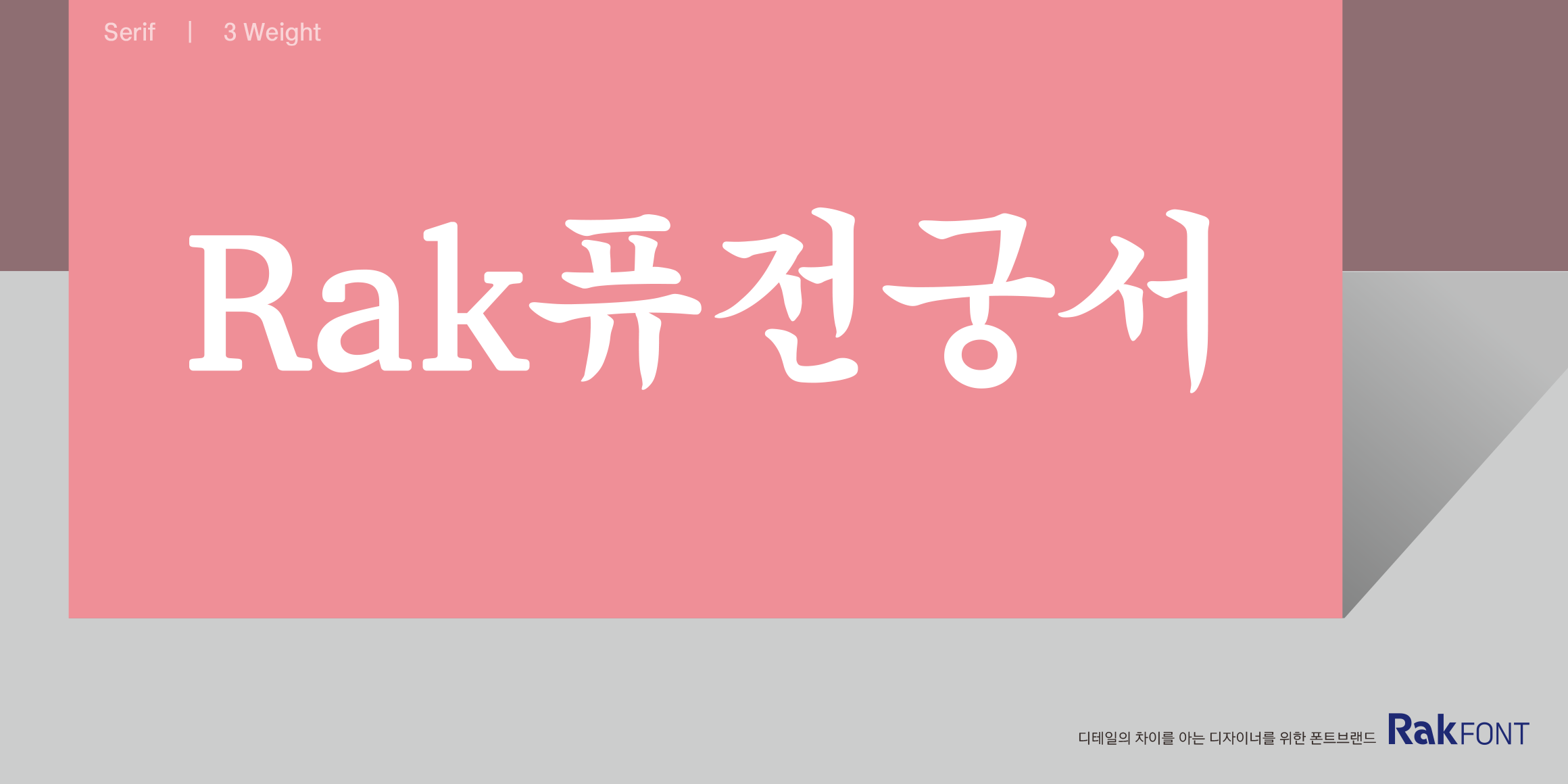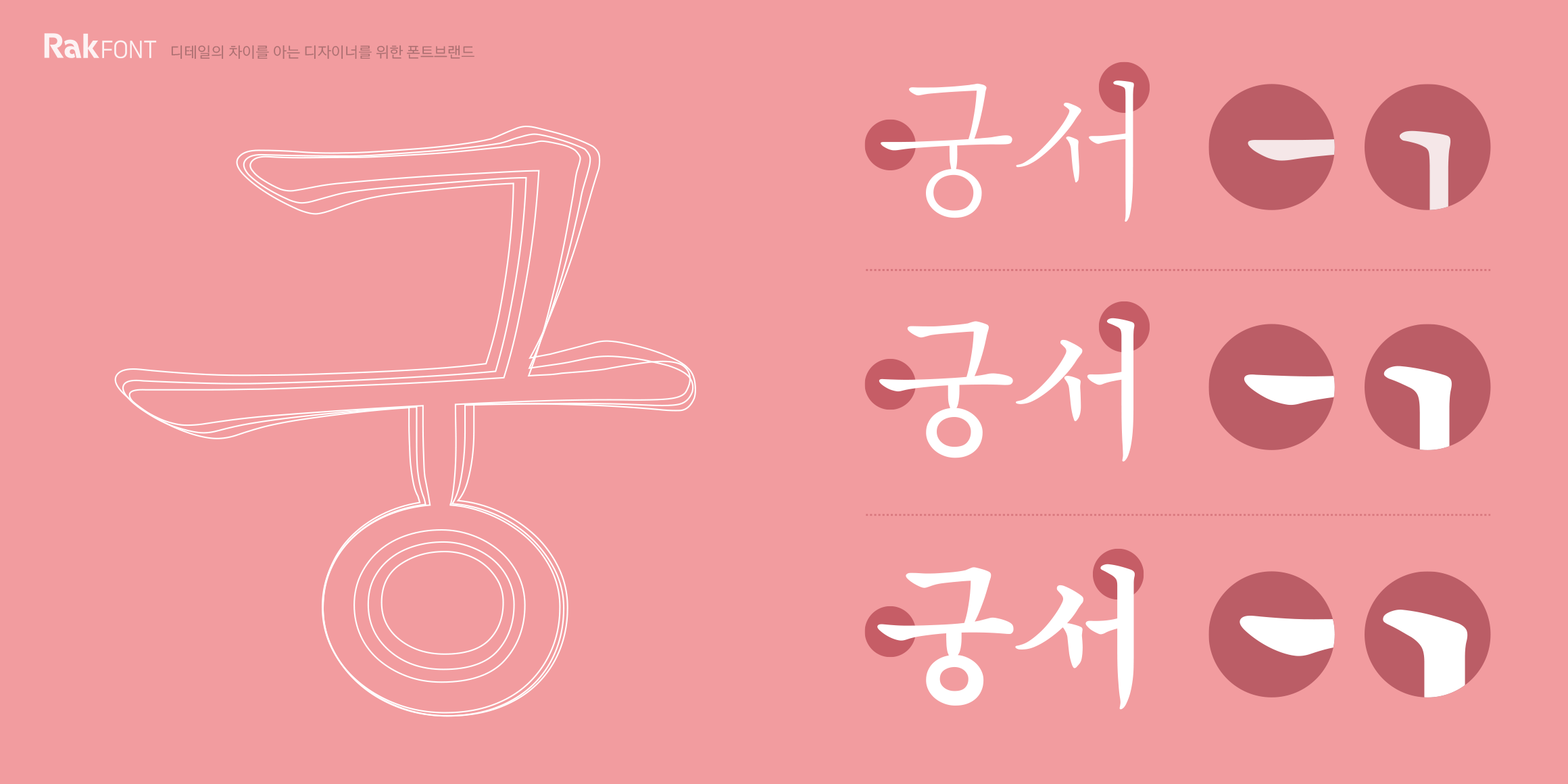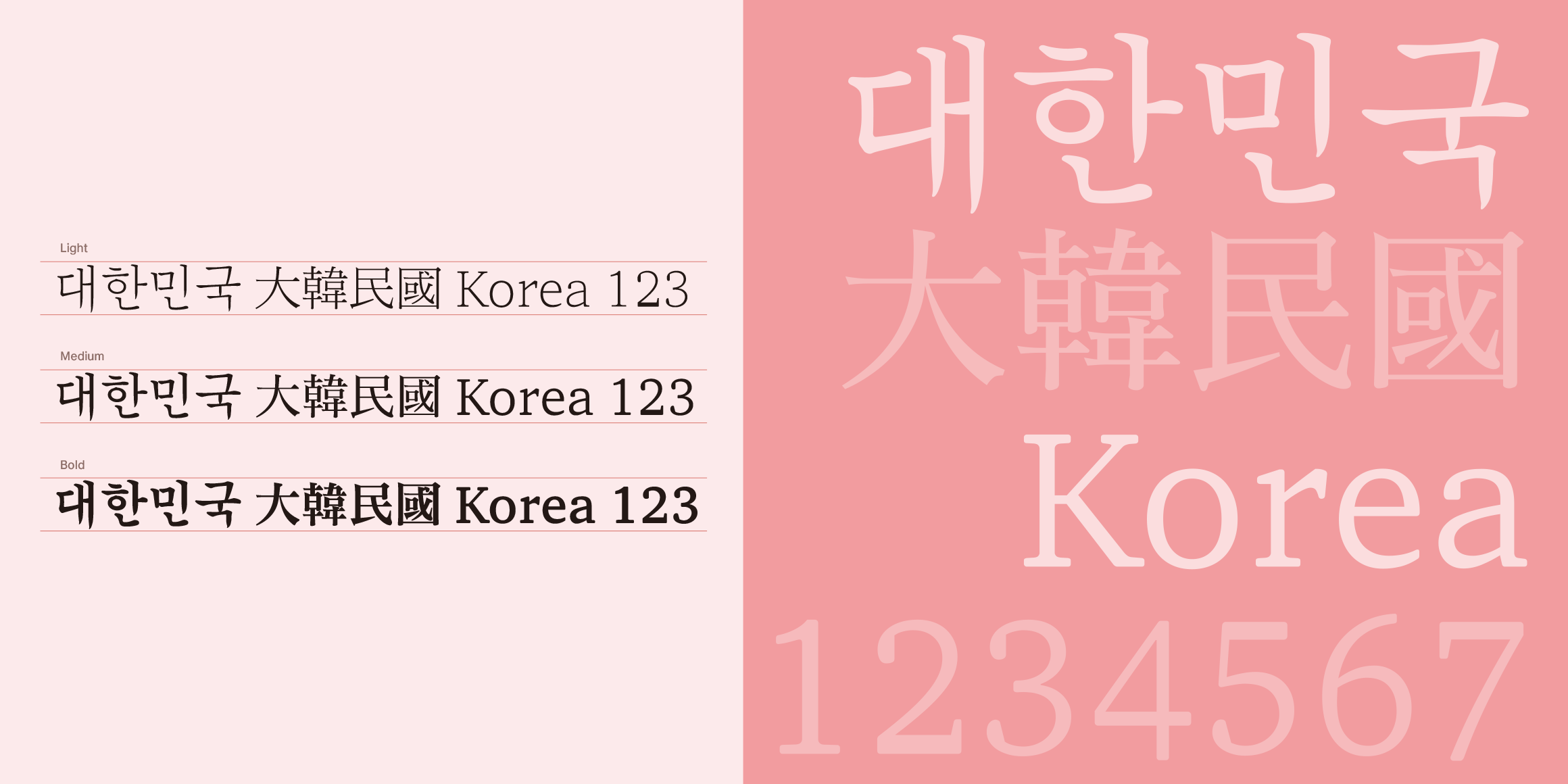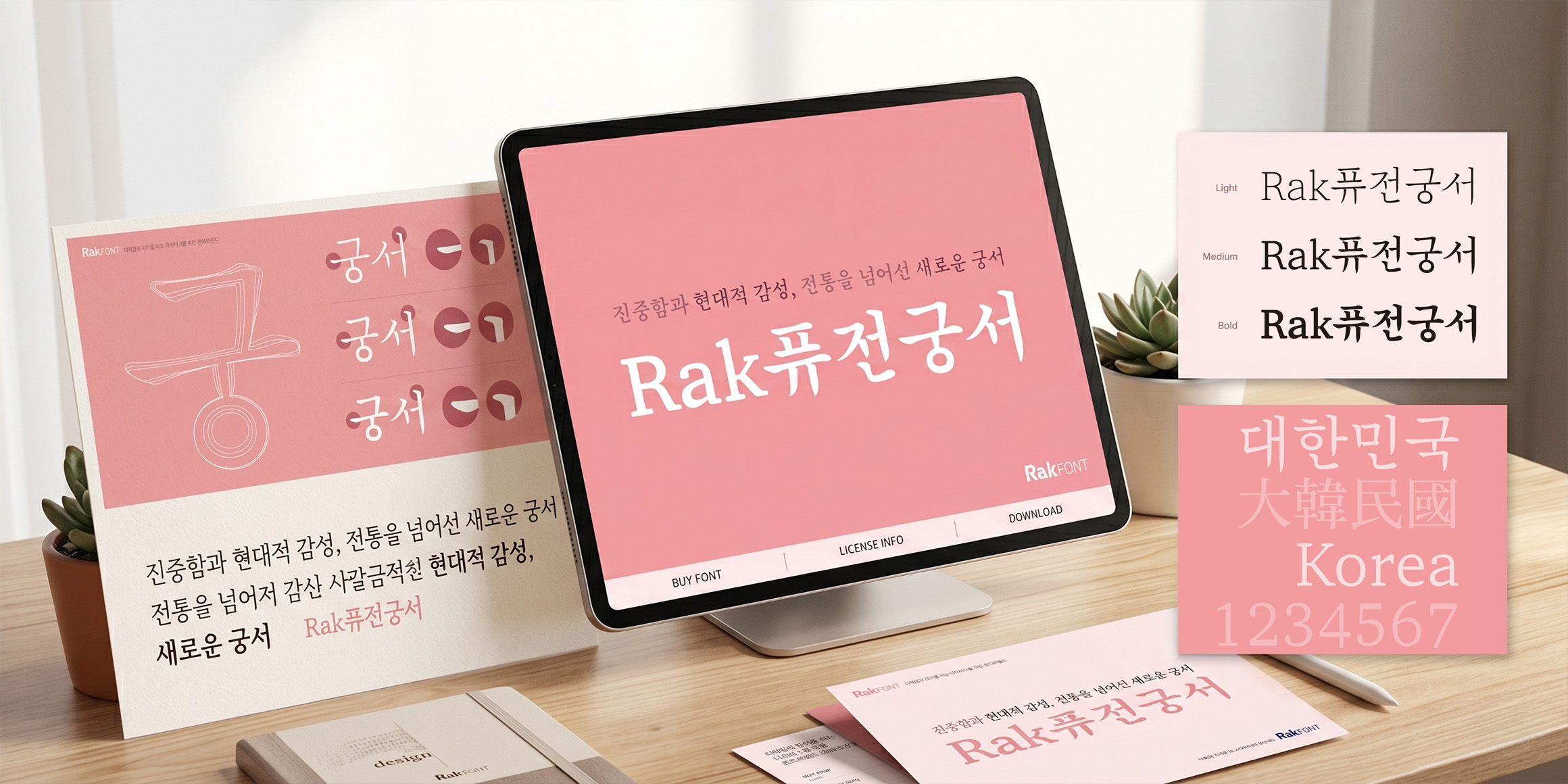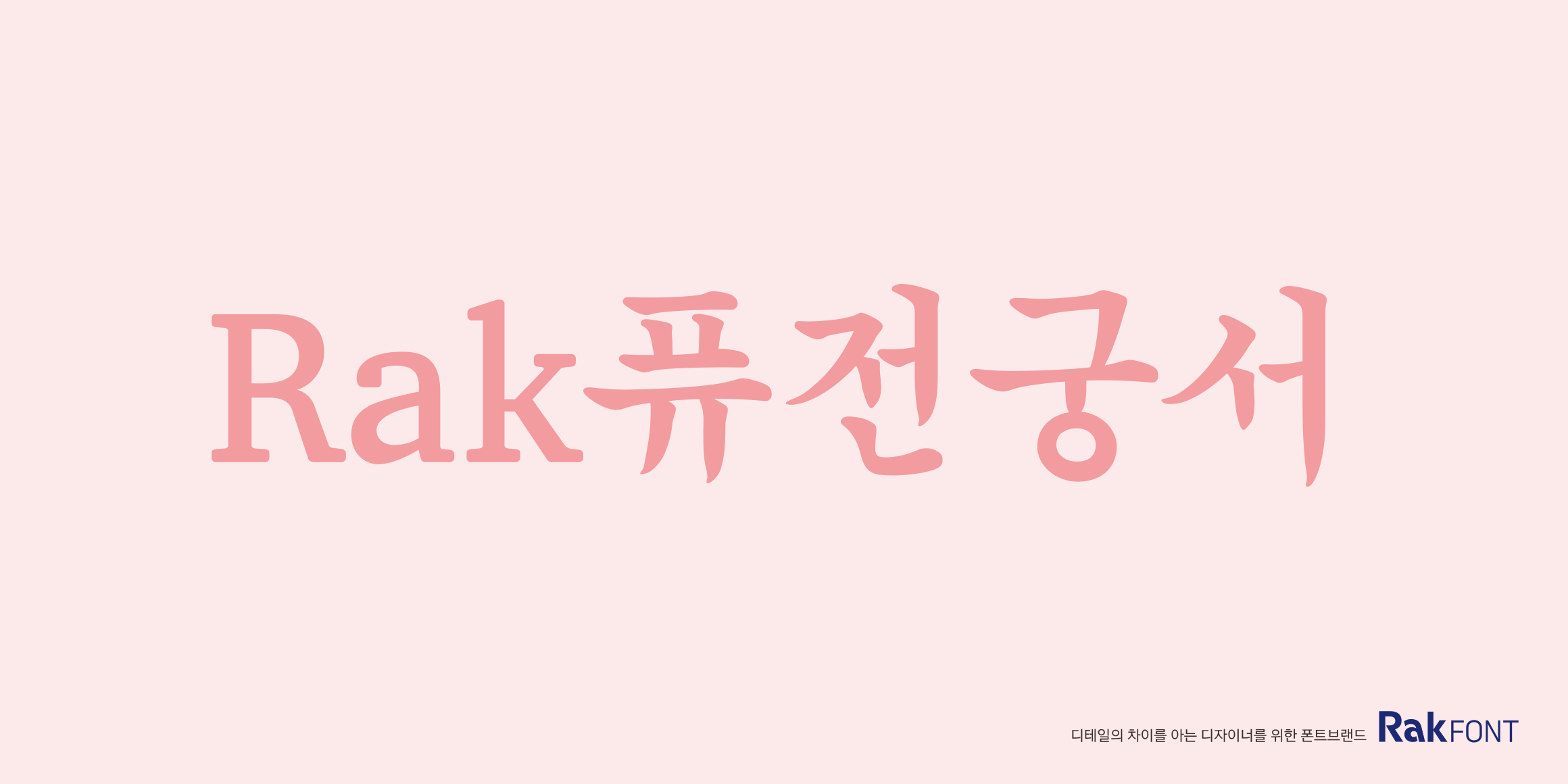
Rak퓨전궁서
분류 Mincho,Serif,부리
'Rak퓨전궁서'는 퓨전 시리즈의 레트로 라인업으로, 전통적인 궁서체의 뼈대 위에 현대적인 감각을 더해 재해석한 폰트입니다. 기존 궁서체의 가장 큰 한계였던 굵기의 제약을 넘어 다채로운 굵기(Weight) 패밀리를 제공함으로써 실무 활용도를 대폭 높였습니다. 궁서체 특유의 진중한 무게감은 유지하되 모던한 세련미를 잃지 않아, 기존 전통 서체의 완벽한 대안이 되어줍니다. 'Rak퓨전궁서'를 통해 한층 더 깊이 있고 고급스러운 현대적 타이포그래피를 구현해 보세요.